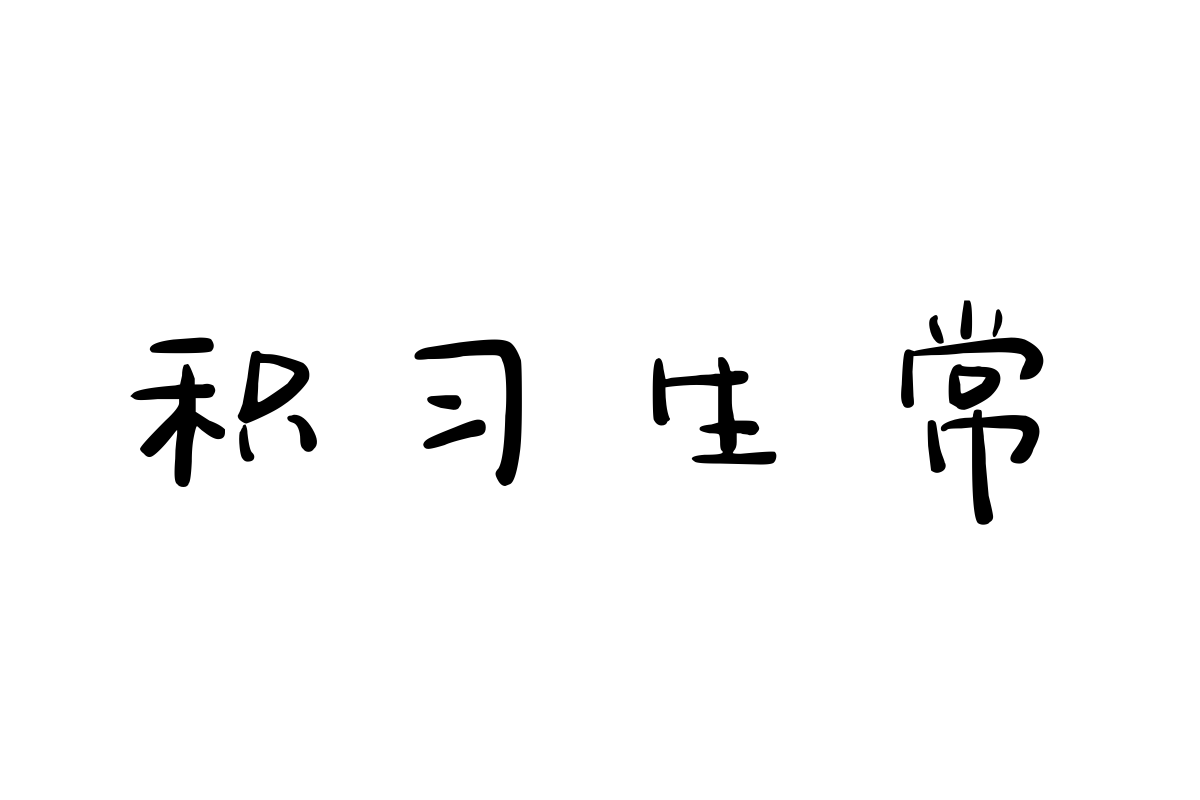
三极诗酒茶赋字体是一款具有独特风格的中文字体,它融合了古典与现代的元素,展现出一种独特的艺术美感。这款字体的设计灵感来源于古代文人墨客的诗意生活,通过巧妙的笔画组合和结构布局,将诗歌、酒、茶三种元素巧妙地结合在一起。
字体特点:
1. 字形优美:三极诗酒茶赋字体的字形流畅自然,线条柔美,给人一种优雅的感觉。
2. 结构严谨:每个字的结构都经过精心设计,使得整个字体看起来既紧凑又富有层次感。
3. 风格独特:这款字体既有古典的韵味,又不失现代的气息,给人一种别具一格的视觉体验。
4. 适用场景广泛:无论是用于书籍、杂志、广告还是网页设计,三极诗酒茶赋字体都能展现出其独特的魅力。
总的来说,三极诗酒茶赋字体是一款非常优秀的中文字体,它不仅具有独特的设计风格,而且能够很好地融入各种应用场景中,为人们提供更好的视觉体验。